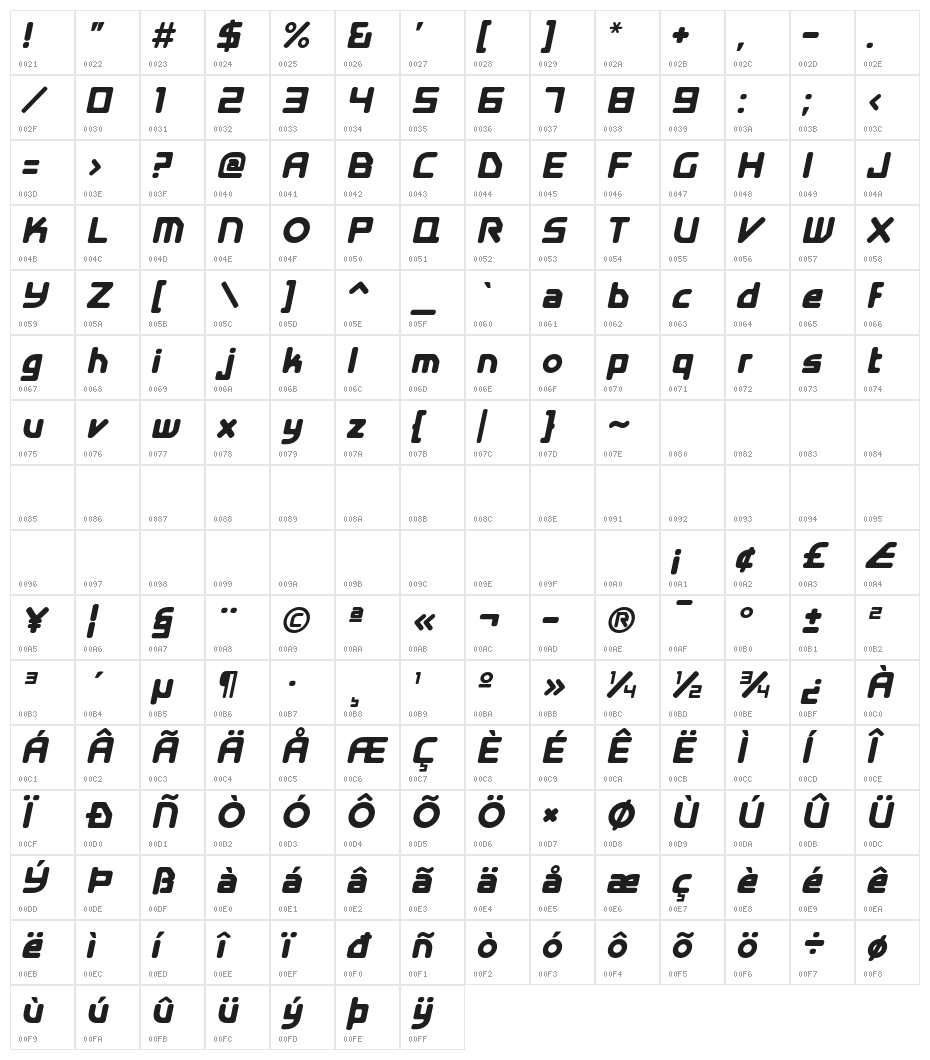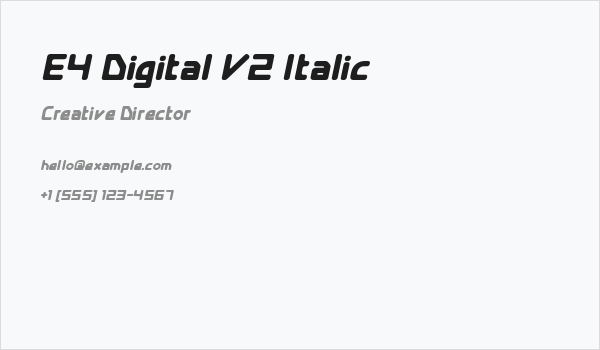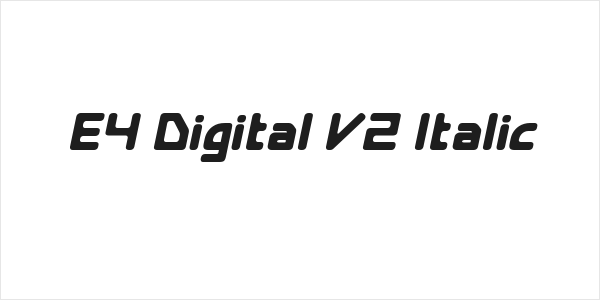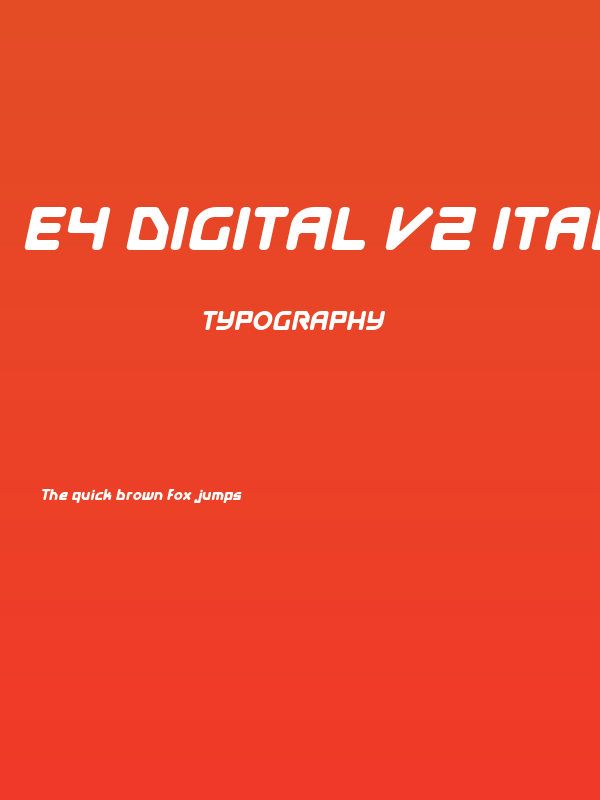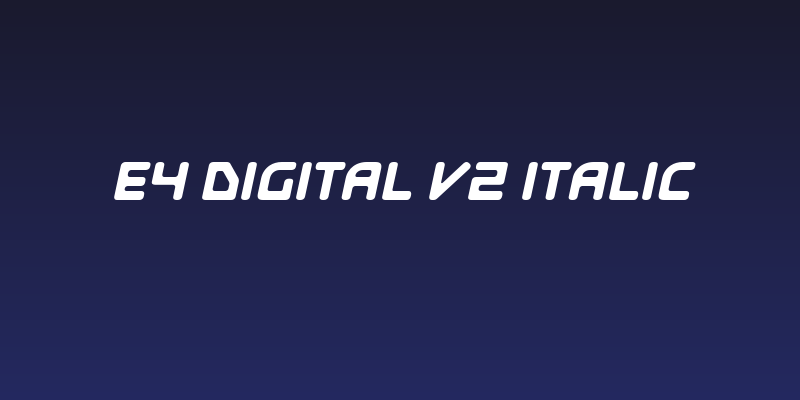
E4 Digital V2 Italic Font
✎ Futuristic
| Anwendungsfall | Headlines, Logos, Digital interfaces |
| Vorgeschlagene Projekte | Ideal for tech branding, digital interfaces, sci-fi themed projects, and modern advertising. |